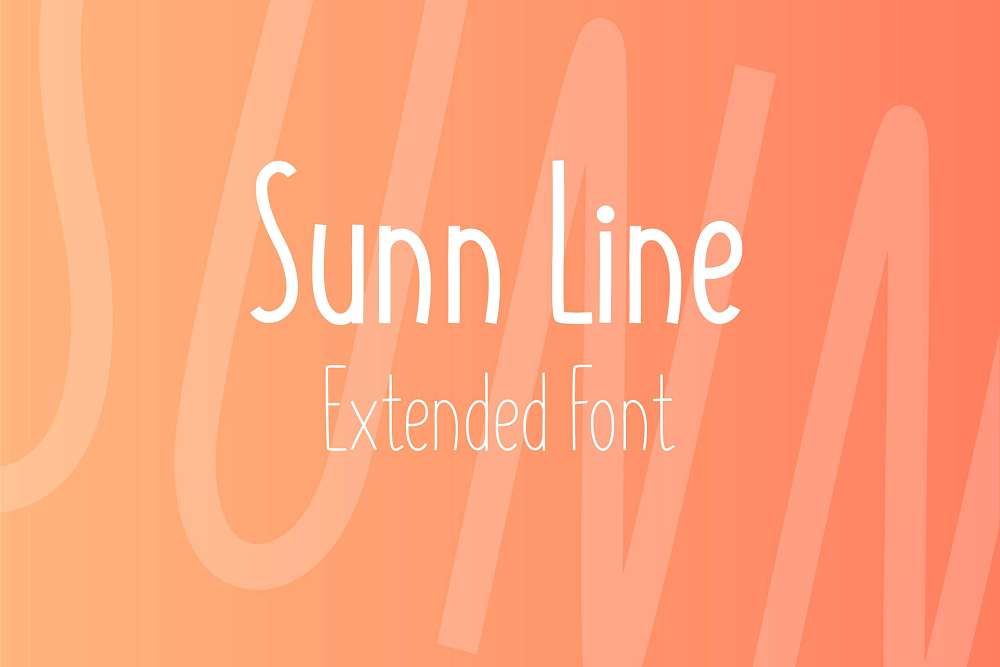
это выразительный дисплейный гротеск от латвийской студии WildOnes Team (автор Gatis Vilaks), выпущенный в 2017 году. Это расширенная версия оригинального семейства SUNN, отличающаяся увеличенной шириной букв и характерным «дрожащим» контуром, имитирующим рукописное начертание маркером или кистью. При этом шрифт сохраняет геометрическую строгость и единый вес линии во всех начертаниях. Шрифт полностью адаптирован для **кириллических** текстов, поддерживая как базовую кириллицу, так и расширенную латиницу (Latin Extended). Благодаря своему игривому, но структурированному характеру, он отлично подходит для создания летней атмосферы, молодежной айдентики и креативных заголовков. Вы можете скачать бесплатно этот шрифт на нашем сайте.